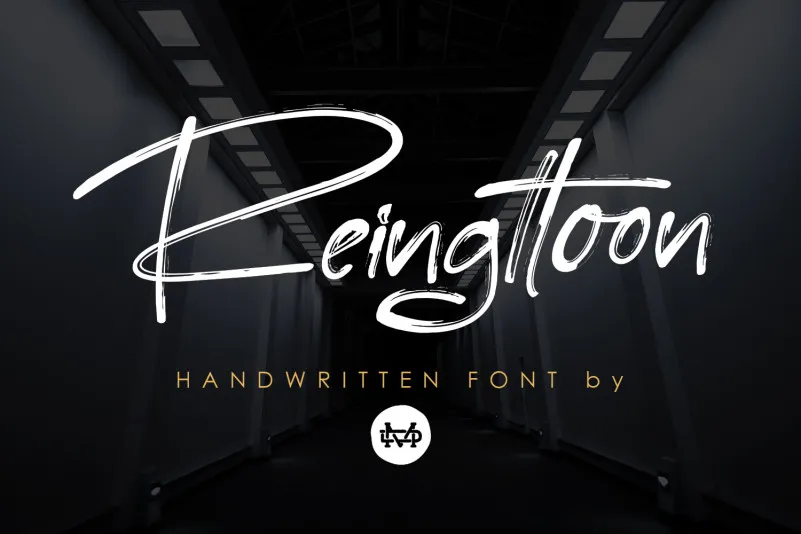
Reingttoon – Handwritten Brush Font – Download Grátis
A fonte Reingttoon – Handwritten Brush é uma criação do designer madeDeduk que oferece uma sensação fluida e criativa para qualquer projeto. Com suas linhas elegantes e leves, a fonte Reingttoon traz um toque moderno de autenticidade aos seus designs. Especialmente perfeita para aplicar em design gráfico como posters, capas de livros, materiais de merchandising, campanhas fashion, mensagens de newsletter, marcas de marca e anúncios, revistas e álbuns, suas características manuscritas e abertas fornecem um toque único aos seus projetos. Com seu estilo cuidadosamente elaborado, a fonte Reingttoon – Handwritten Brush é perfeita para tornar uma mensagem pessoal e única. Seja através de um design de quote ou qualquer outro tipo de projeto gráfico que exija uma escrita manuscrita elegante e autêntica, esta fonte será sua melhor escolha. A Reingttoon – Handwritten Brush é a escolha perfeita para quem busca criar designs com um toque sofisticado e criativo.